Untuk meningkatkan daya tarik desain, gaya font yang dipilih harus menarik dan unik. Ada banyak pilihan font dan gaya huruf seperti font script yang seperti tulisan tangan. Untuk menciptakan desain yang lebih menarik, perhatikan tips memilih jenis font script sesuai kebutuhan.
Font script yang seperti tulisan tangan akan terlihat alami dan memiliki gerakan halus seperti tulisan tangan. Style font ini ada yang memiliki huruf bersambung dan tidak. Aga font script mudah dibaca dan relevan, penting untuk dipilih gaya huruf sesuai kebutuhan desain.
GAYA HURUF FONT SCRIPT
Font script adalah font yang memiliki gaya huruf seperti tulisan tangan menggunakan brush atau pen untuk kaligrafi. Untuk itu gaya hurufnya memiliki banyak variasi dari yang formal, elegan hingga bulat. Ciri-ciri font script umumnya:
- Memiliki variasi ketebalan dan lebar guratan
- Memiliki garis huruf melengkung
- Huruf mengalir, halus dan tampak alami
Setiap gaya huruf yang memiliki guratan garis berbeda ini bisa menciptakan kesan berbeda sehingga perlu dipilih dengan bijak. Umumnya font script ini bisa mudah beradaptasi untuk berbagai kebutuhan desain. Font script juga menciptakan berbagai emosi dari yang feminin, elegan, formal hingga ramah.
TIPS MEMILIH JENIS FONT SCRIPT YANG SESUAI KEBUTUHAN
Pastikan menggunakan gaya huruf script sesuai kebutuhan desain sehingga menciptakan desain yang menarik dan relevan. Ada banyak variasi gaya huruf script dari yang elegan, bulat hingga tebal. Dalam memilih yang sesuai, perhatikan tips menyesuaikan kebutuhan jenis desain dan pesannya.
Gunakan Gaya Huruf Tipis
Style font script yang seperti tulisan tangan ini cukup bervariasi, meskipun begitu kebanyakan memilih huruf bersambung atau latin. Huruf bersambung terkadang sulit dibaca jika bentuk hurufnya terlalu rapat, tebal atau terlalu panjang.
Jika memiliki huruf latin gunakan gaya huruf tipis bila ingin tampil elegan. Gaya huruf tipis juga akan cocok digunakan pada desain feminim dan mewah. Jika gaya hurufnya cukup rapat, maka font tipis akan lebih mudah dibaca daripada font tebal.
Gaya Huruf Bulat untuk Menciptakan Desain Ramah
Ada juga style font script yang bulat dan memiliki gaya huruf yang agak tebal. Untuk memastikan tipografi terbaca dengan baik, ada tips memilih font bulat bergaya script.
Font bulat harus bersih, tidak terlalu tebal, dan antar hurufnya memiliki jarak yang cukup. Pilih gaya font script bulat untuk menciptakan kesan desain dan branding ramah.
Pilih Gaya Huruf Handwritten agar Berkesan Personal
Sementara itu gaya font handwritten akan tampil lebih personal dan seperti tulisan tangan karena tidak serapi font script latin yang formal. Gaya tipografi handwritten cocok dipilih untuk membangun branding yang ramah.
Tips memilih font script untuk gaya tulisan tangan ini sebaiknya pastikan hurufnya sederhana, mudah dibaca dan tidak terlihat terlalu berantakan. Seringkali gaya handwritten ini akan digunakan untuk jenis brand ramah seperti brand untuk anak-anak, makanan dan handcrafted.
Pilih Gaya Huruf yang Mudah Dibaca
Font script seringkali memiliki jarak huruf yang terlalu padat sehingga bisa sulit untuk dibaca jika terlalu rapat. Tetapi font script juga tidak bisa diubah tracking dan kerningnya karena akan terlihat buruk.
Untuk itu perhatikan tips memilih font script latin yang memiliki ruang negatif yang cukup, bentuk huruf sederhana dan tidak memiliki dekorasi serif yang terlalu panjang. Pilih font script yang memiliki jarak yang cukup agar terbaca dengan baik dan efektif menyampaikan pesan.
Gunakan Font Tebal untuk Menciptakan Kesan Klasik dan Retro
Jenis font script yang memiliki huruf tebal ada yang tampil tajam ada juga yang tampil bulat. Font script yang memiliki style tajam dan tebal akan menciptakan kesan klasik atau tradisional seperti font blackletter. Tips memilih font script tebal harus disesuaikan tema desain atau pesan yang ingin disampaikan.
Biasanya font blackletter akan digunakan untuk tema heritage klasik, cocok juga untuk desain branding fashion streetwear atau logo barbershop. Sementara gaya script bulat dan tebal akan memiliki kesan tipografi bergaya retro. Font tersebut akan cocok untuk desain brand bakery atau brand tradisional lainnya.
GAYA HURUF SCRIPT UNTUK BRAND YANG RELEVAN
Agar desain brand tampil menarik dan relevan, penting untuk tahu tips memilih gaya huruf script sesuai jenis brand. Setiap gaya huruf script akan menciptakan kesan berbeda dan dapat digunakan untuk merepresentasikan karakter brand yang berbeda. Font script memilih 5 gaya huruf yaitu formal, casual, handwritten, calligraphic dan blackletter.
Script Formal untuk Desain Elegan dan Mewah
Gaya script ini termasuk yang paling sederhana, mudah dibaca dan digunakan untuk berbagai desain. Gaya hurufnya cukup tipis dan memiliki jarak antar huruf yang cukup sehingga mudah dibaca. Font ini tidak memiliki garis yang panjang sehingga tidak terlalu mengganggu keterbacaan.
Pilih font formal ini untuk menciptakan desain elegan, formal dan mewah. Gaya huruf tipis dan guratan halus menciptakan tipografi bersih yang mudah dibaca. Biasanya banyak digunakan untuk desain undangan pernikahan dan logo fashion mewah.
Script Casual untuk Brand Ramah dan Menyenangkan
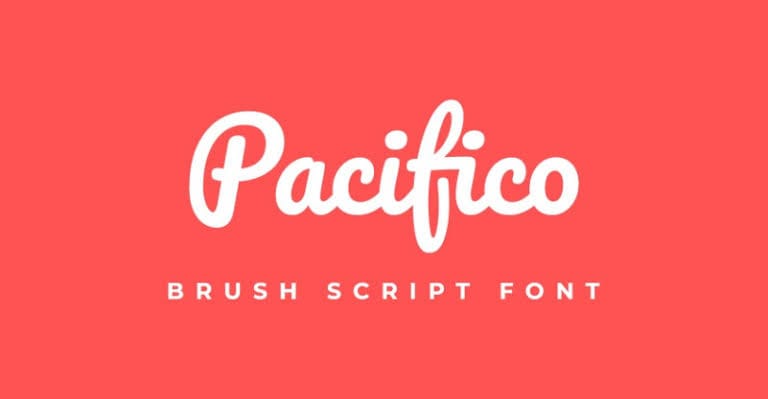
Sementara itu pilih gaya font script bulat dengan sudut melengkung ini untuk menciptakan kesan brand yang ramah dan menyenangkan. Style font tebal dan bulat ini akan lebih mudah dibaca daripada style huruf yang tipis. Gaya font casual ini akan merepresentasikan brand yang ramah sehingga cocok untuk logo brand anak-anak.
Font script casual ini juga akan relevan untuk tipografi logo makanan atau minuman karena memiliki font tebal yang berkesan menyenangkan. Perhatikan dalam memilih ketebalan hurufnya agar tidak terlalu tebal hingga sulit dibaca. Gaya huruf bersambung tidak boleh terlalu tebal karena akan terlihat padat dan bisa sulit terbaca.
Baca juga: Rekomendasi Gaya Font untuk Tipografi Logo Fitness dan Sport
Handwritten untuk Brand Makanan dan Minuman
Untuk font yang memiliki gaya huruf seperti tulisan tangan ini tampil lebih alami seperti tulisan tangan pada umumnya. Terkadang gaya hurufnya memiliki ketebalan dan ukuran yang tidak konsisten. Gaya huruf ini akan cocok untuk desain branding brand personal atau logo pribadi seseorang.
Font handwritten juga bisa digunakan untuk menciptakan tema elegan pada brand skincare atau fashion. Pada jenis desain undangan atau kartu ucapan, gaya font ini juga akan relevan. Gaya font tipis akan menciptakan desain elegan dan feminim, sementara handwritten yang tebal akan berkesan ramah. Biasanya font ini sering digunakan untuk brand makanan dan minuman.
Calligraphic Untuk Desain Feminim
Jika ingin menciptakan desain yang bergaya feminim dan elegan gunakan jenis font script kaligrafi. Namun perhatikan tips untuk memilih font calligraphic yang tipis dan bersih agar mudah dibaca. Garis huruf pada font ini akan memiliki desain yang elegan sehingga cocok untuk logo fashion dan kecantikan.
Gunakan gaya font ini untuk target pasar perempuan karena akan relevan dengan preferensi mereka. Terutama gunakan font pada desain logo yang minimalis dan elegan sehingga harmonis.
Blackletter Untuk Branding Vintage dan Heritage Brand
Ada juga style font tebal dan tajam yang memiliki dekorasi garis-garis tipis yang akan tampil menonjol. Style font script ini cukup unik sehingga bisa digunakan sebagai desain logo tanpa perlu tambahan ikon. Penggunaan font ini cocok untuk branding fashion streetwear, logo barbershop hingga logo cafe klasik.
Font klasik ini akan menciptakan nostalgia dan kesan brand yang unik. Cocok untuk digunakan pada desain bertema klasik, retro dan vintage. Gaya font bisa menciptakan kesan tegas sehingga bisa digunakan untuk logo sport seperti klub olahraga.
Banyaknya style font script akan menciptakan berbagai kesan dan kesan yang berbeda, sehingga harus disesuaikan kebutuhan. Tips untuk memilih font script yang tepat dengan mengetahui jenis gaya hurufnya dan disesuaikan dengan pesan brand. Pilih gaya huruf yang paling relevan untuk mewakili karakter dan pesan brand.